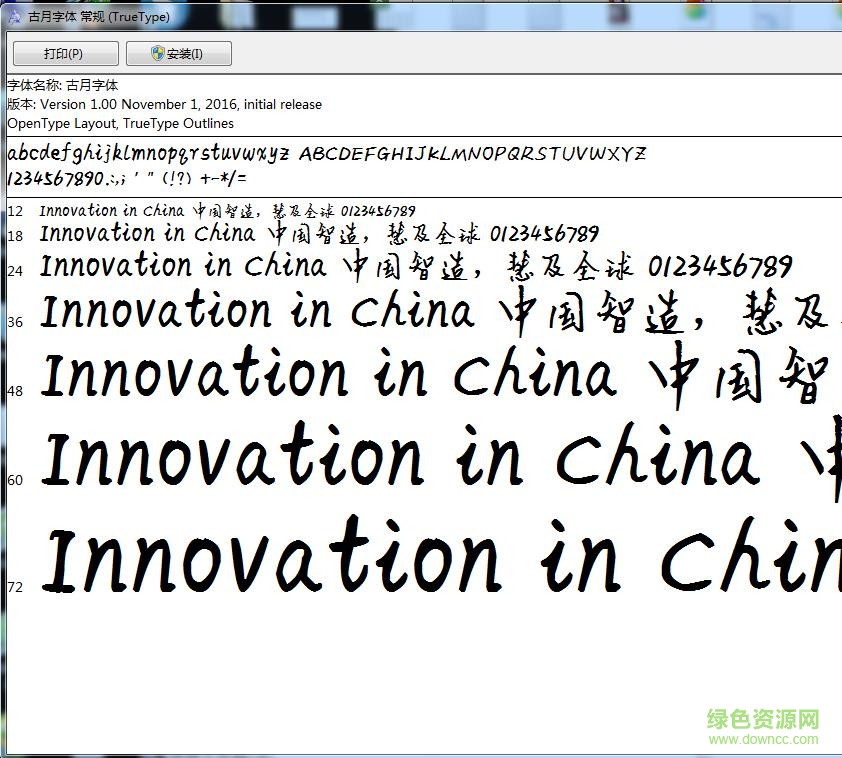
神韻古月體字體受到了眾多用戶的喜愛,運(yùn)用十分廣泛,在手機(jī)上進(jìn)行聊天交友,在電腦上進(jìn)行藝術(shù)字創(chuàng)作,媒體制作等,還能夠運(yùn)用到書帖當(dāng)中讓喜愛這款字體的用戶進(jìn)行臨摹學(xué)習(xí),十分不錯(cuò),你值得擁有!
這款字體在我使用的許多字體中個(gè)性十分鮮明,讓你一眼就能認(rèn)出者款古月體,擁有很不錯(cuò)的展示效果,你可以來常識(shí)以